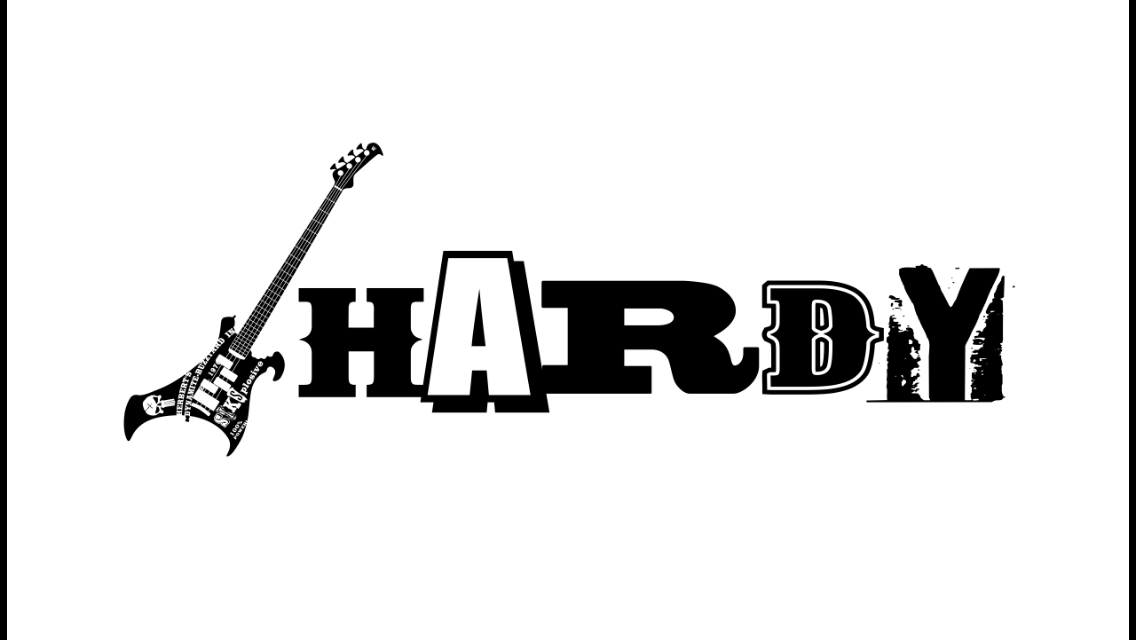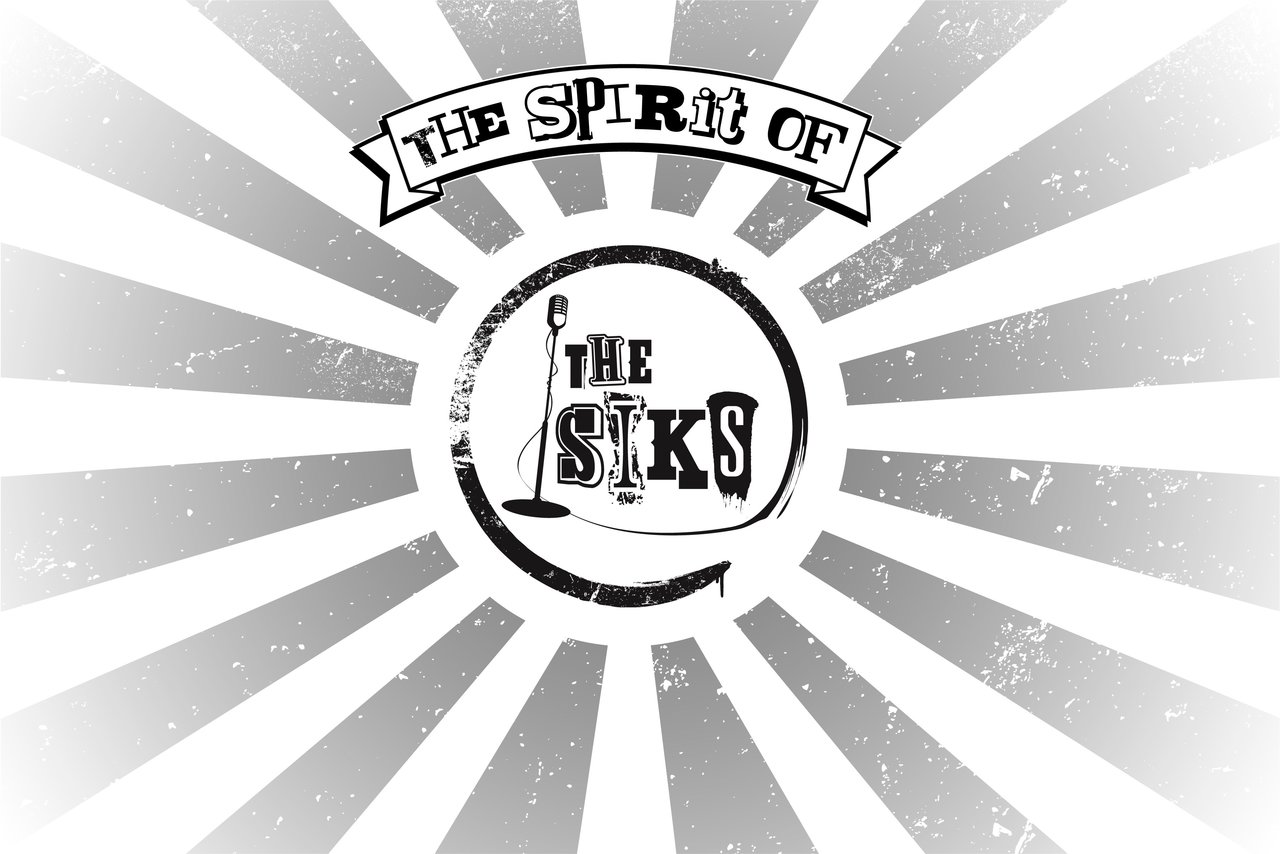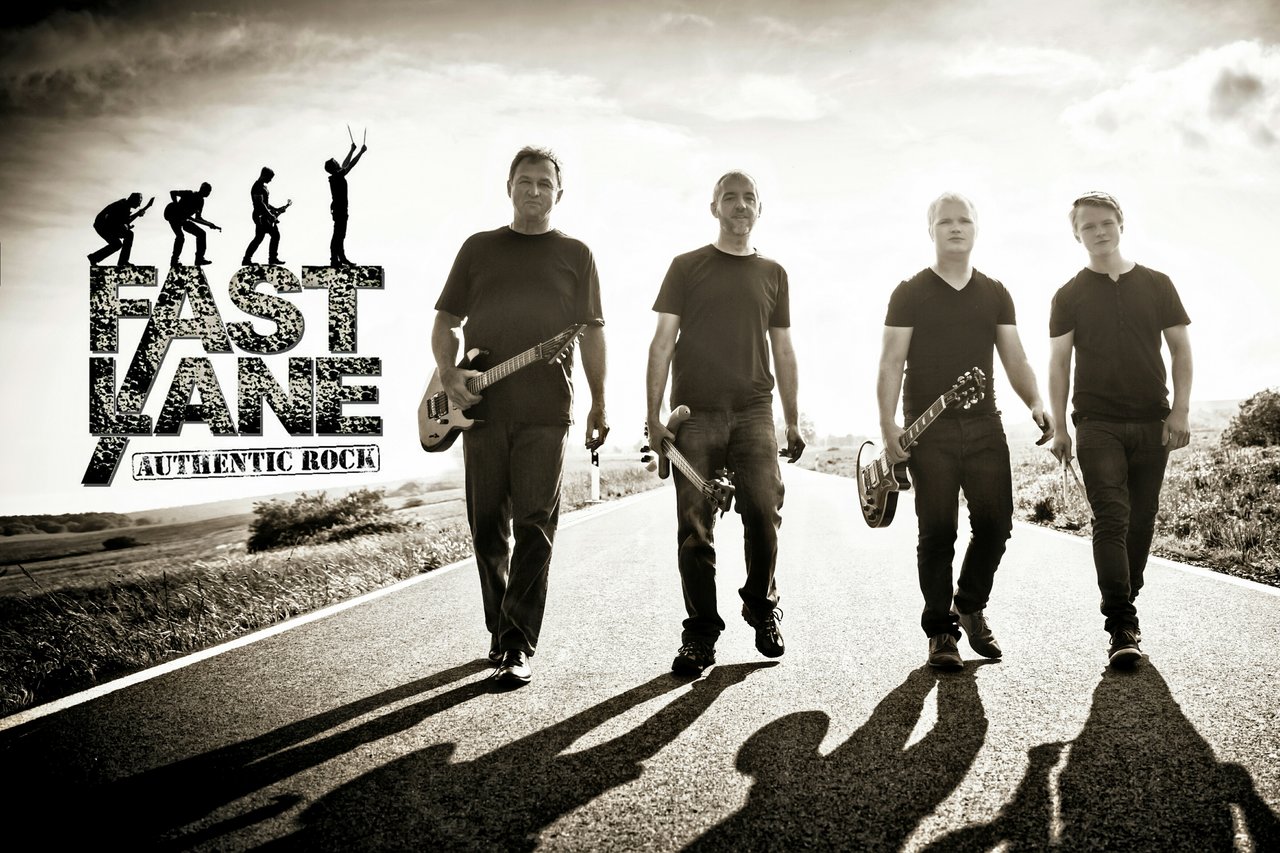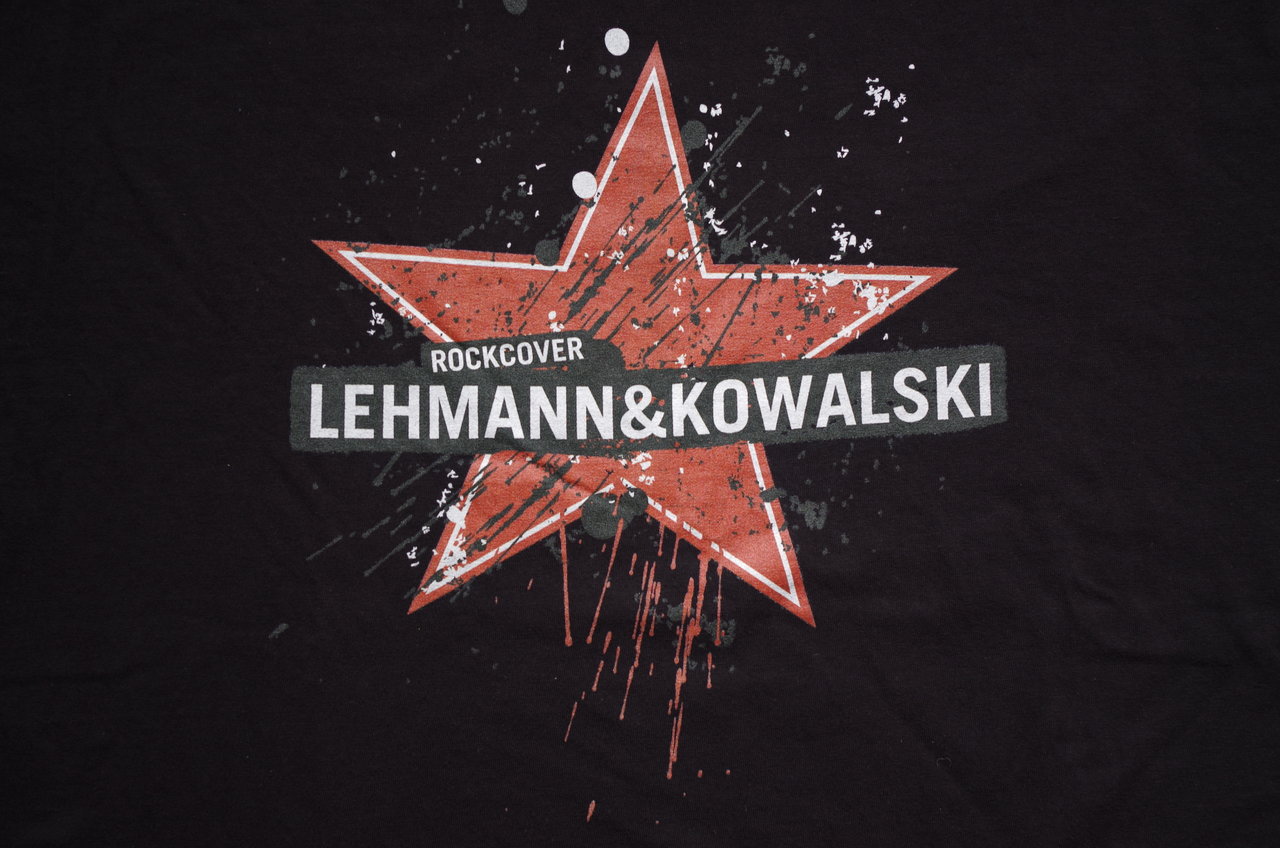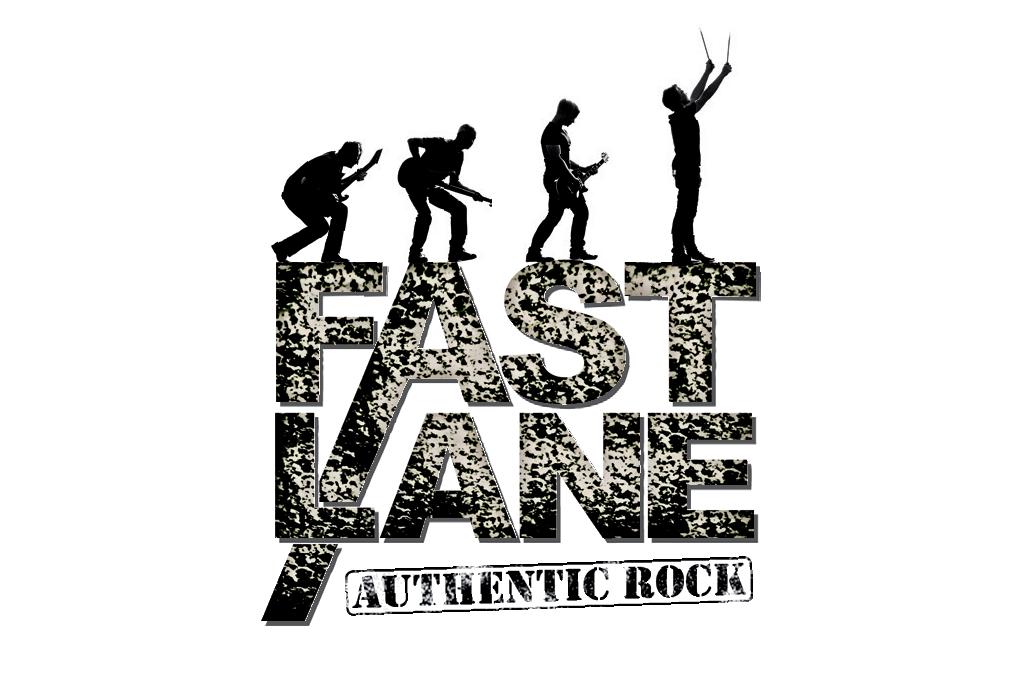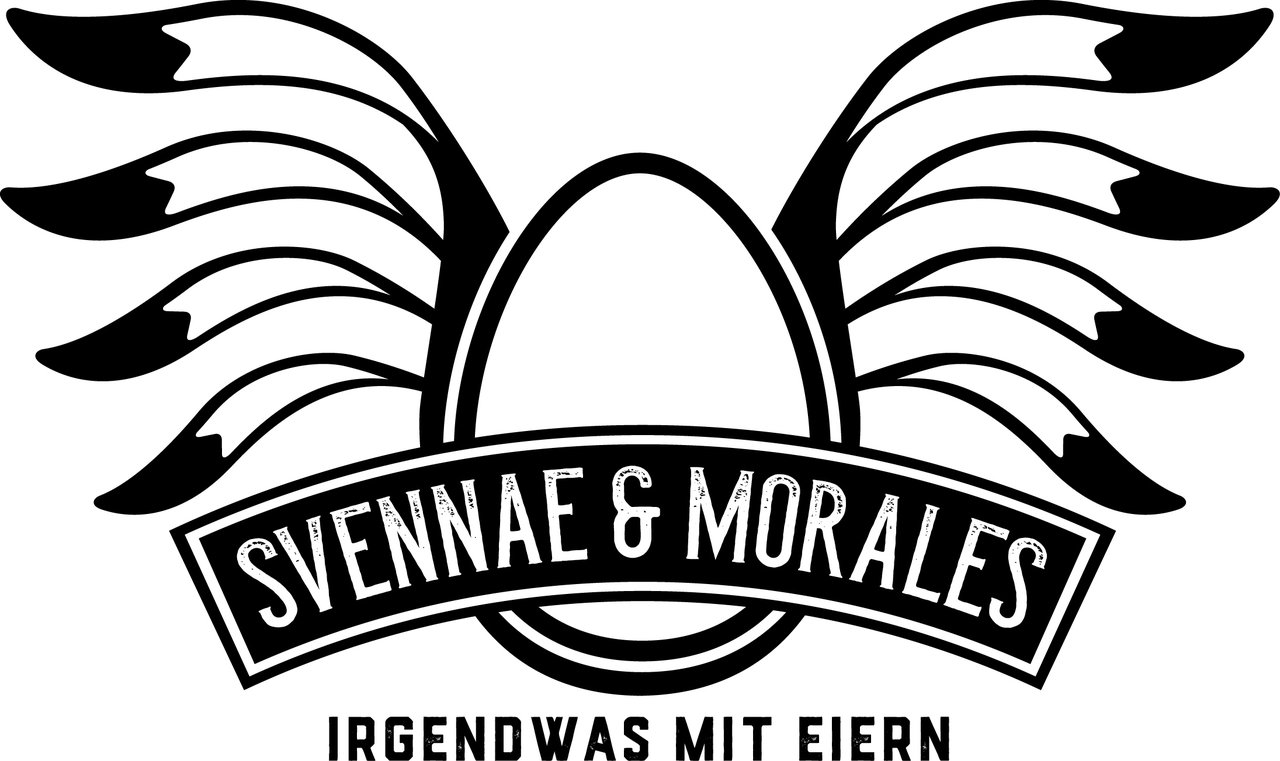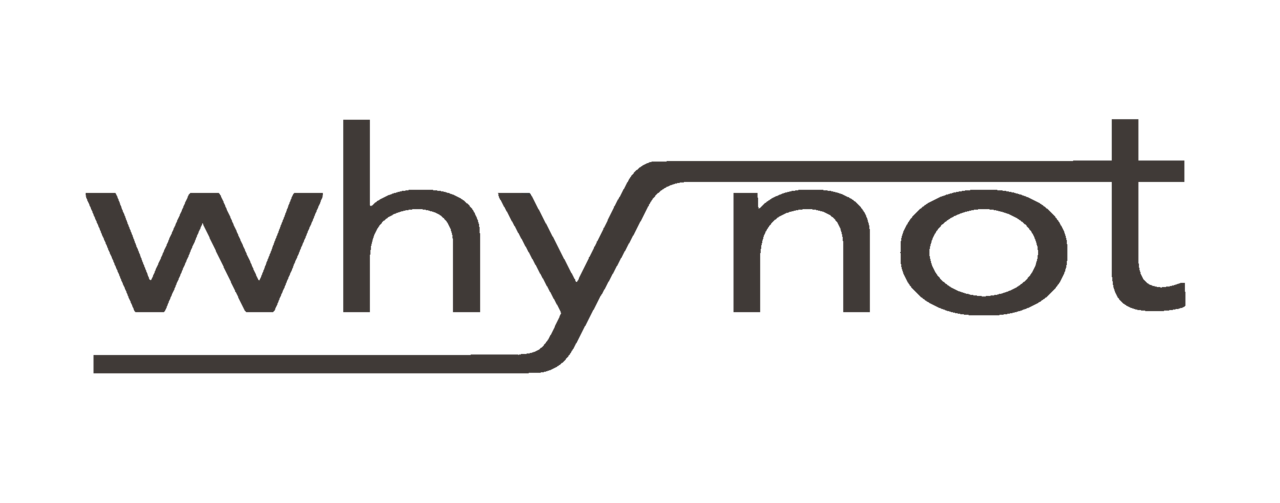
Euer Bandlogo-Artwork-Schriftart... her damit...!
Die Band gabs schon, als ich einstieg. Der Bandname ergab sich -so hörte ich- irgendwie am Biertisch
Zu der Entstehung des Logos:
Unsere Band setzt sich aus sehr unterschiedlich "jungen" Musikern zusammen.
Der Jüngste ist 19, der älteste kurz über 60.
Wir wollten diesen Altersunterschied und den gleichmäßig beliebten Musikgeschmack irgendwie rüberbringen.
Einer der ganz jungen hatte dann diese Evolutions-Idee.
Sicher nix Neues.
Haben uns dann mit der Idee und einer aufgeschlossenen Fotografin in die nahen hohen Berge gemacht und einfach drauf losgeschossen.
Sie wollte die Fotos spätnachmittags mit viel Gegenlicht bei niedrig stehender Sonne machen.
Nebenbei entstand dann noch ein schönes Bandplakat:
Der Name entstand aus Ideenlosigkeit. ;-)
Einfach mal den Songordner geblättert:
Life in the Fast Lane....
Die Fotografin hat dann den Schriftzug gestaltet.
O.K., hier ist unser Design. Entworfen von einem befreundeten Künstler, der uns tatsächlich eine eigene Type entwickelt hat und uns einiges an Vorlagen liefern kann.
Die Beschriftung meines Basses einschließlich des modifizierten Punisher-Skulls stammt ebenfalls von ihm.
Der Jüngste ist 19, der älteste kurz über 60.
Why not gibt's viele...
Auch bei uns im Raum gab's mal 'ne Why Not Skiffle Band...
Why not gibt's viele...
Auch bei uns im Raum gab's mal 'ne Why Not Skiffle Band...
Das ist immer so ein Thema. Solange die Band lokal bleibt, ist eine Namensgleich heit mit anderen Bands kein Problem. Wenns überregional wird oder finanzielle Interessen berührt sind, kanns dann auch mal Probleme geben. Wo kein Kläger, da kein Richter. Aber auch der Umkehrschluß gilt... Deshalb ist es of so schwer, einen noch nicht vergebenen coolen Namen zu finden. 80-90% unserer seinerzeitigen Namenseinfälle waren schon belegt (Recherche: Google, div. Bandregister, Youtube, Facebook, Soundcloud...)...
Vendigo ist mein Hauptding. Kurzgesagt, ne Art QOTSA mit bisschen proggy Zeuch.
Der Name kommt aus einer Art indianischem Werwolf-Glauben, bzw. dann spielen noch vampiristische und kannibalistische Dinge eine Rolle, das variiert halt lokal. Im Original wird das meisst "Wendigo" geschrieben.
Wichtig war dass der Name ein Name ist. Ein Wort, unter 8 Buchstaben. Keine Wortkombinationen, die finden wir alle doof. Das mit dem indianischen Einflüssen für den Namen fanden wir sehr passend und vergleichsweise unverbraucht für psychedelische Musik.
Einfach besser als noch irgendwas mit "Stoner, Dope, Weed, Desert, Black, Witch, Acid..." Und irgendwas "lustiges" wollten wir auch auf gar keinen Fall. Ich nehm mir da mal raus einen ersten Tipp zu geben: Wortkombinationen sind unkreativ und lustige Namen sind in mehr als 99 % der Fälle nicht lustig. Viele meinen sie könnten beim Namen irgendwie übertreiben und das dann ironisch mit nem Augenzwinkern rüberbringen. ("Super Flashy Space Hamsters from Orion") Nein. Das Augenzwinkern kommt nie rüber.
Weiter wichtig war dass der Name geschrieben gut aussieht und relativ eindeutig ist wie man ihn ausspricht. Da wär auch zweiter Tipp für alle Suchenden: In Zeiten des Internets ists super gut wenn sich der Name gut liest. Der wird 1.000 mal öfter gelesen als ausgesprochen, ist einfach so.
wolves-image.webp The Original Chicago-Blues From Munich ....
Der Bandname ist entstanden als ich gerade weggehört habe … :bier:
Logischerweise ist das Logo im Februar entstanden.